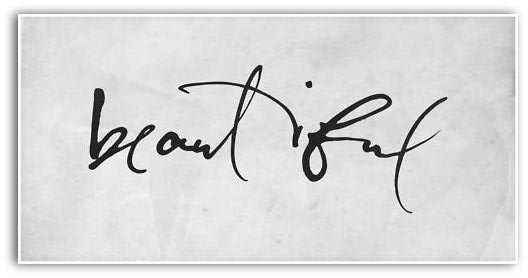
Wie heißt diese Schrift (Beautiful)
Ich suche verzweifelt nach dem Namen dieser Schriftart und werde einfach nicht fündig - KANN MIR BIIIITTTEEE JEMAND HELFEN.
Das sieht einfach handgeschrieben aus, es wird dazu keine Schrift geben.